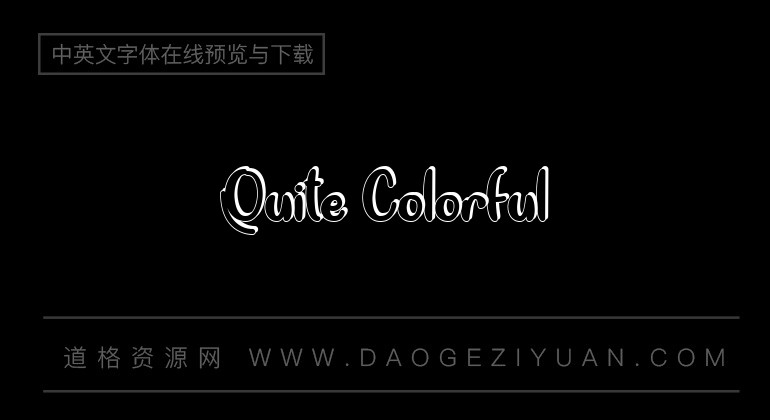
Quite Colorful
Quite Colorful 是一款多功能的字体,其特点是具有活泼而鲜艳的色彩,能够创造出多种不同的风格。它可以用于广告、海报、品牌标识、网页设计等,为设计师和个人提供了灵活的可能性。它的特色是拥有极具表现力的字体,可以让你的设计充满活力和色彩,从而吸引更多的客户。
Quite Colorful是一款非常不错的手写艺术字体,具有很好的视觉感,适合于文化类的宣传设计、商业类品牌的广告和产品包装设计以及个性化文字排版等较多场景。